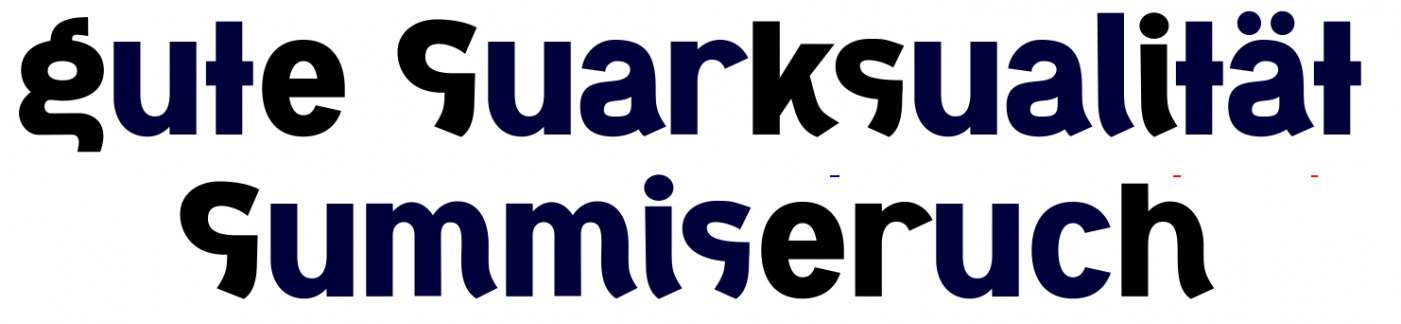
War so etwas in zwei Höhen üblich?
Es könnte sein, dass es für verschiedene Rahmengrößen und verschiedene Linienstärken gedacht war.
Und ich rate jetzt auch mal ins Blaue hinein: Die Sortierung in den 3 Kästenn ist ja ...m n o p r s t... und  ...M N O P R S T...
Sollte das etwa das zugegeben total ungewöhnlich q / Q dieser Schrift sein?
Bei mir schon ... gehören wirklich eindeutig zu der Schrift. Gibts denn nicht irgendein altes Schriftmuster, wo alle Glyphen drin sind und vielleicht sogar in Verwendung gezeigt werden?
Ich fuhr heute an einem Reklameschild vorbei...
Und da fiel mir das R ins Auge...
Ist aber verkehrt herum...
Mich lässt das Ding nicht los...
Könnte man daraus Prozentzeichen (%) bauen?